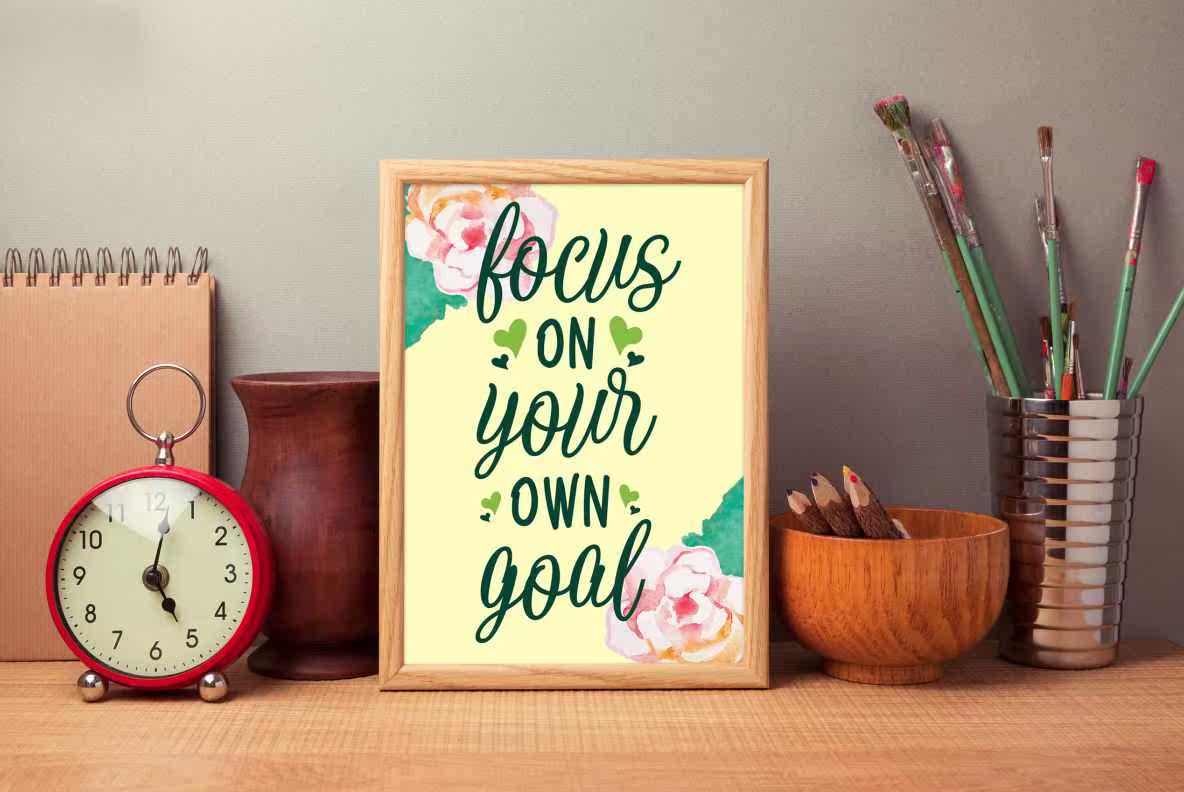
简介BATTALLIONFONTDUO。现代拼音脚本和手写字体之间的有效组合。您可以使用主脚本进行操作。它可以是纯样式或带有PentypeFeatures的Bouncystyle。您可以将此字体用于引号、徽标、婚礼提示、,LoveLetter和Manymore。简介BattallionFontDuo。现代AlligraphyScript和手写字体之间的有效组合。您可以使用主脚本。它可以是纯字体,也可以是带有PentypeFeatures的Bouncystyle。您可以将此字体用于引号、徽标、婚礼激励、LoveLetter和Manymore。